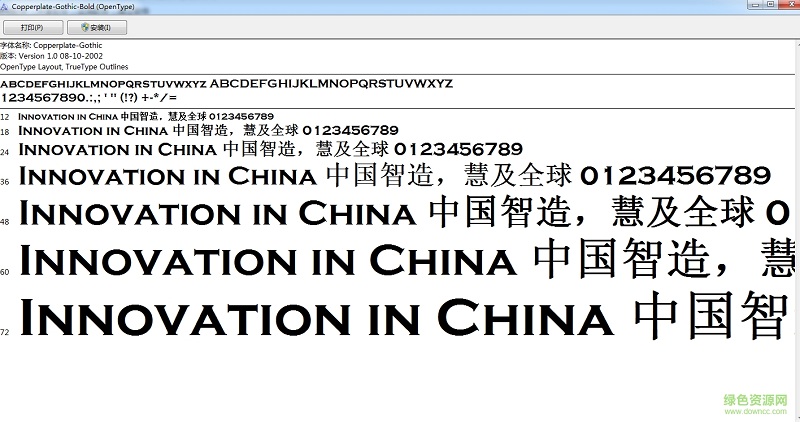
copperplate gothic bold這個(gè)字體是免費(fèi)的英文字體,字體粗黑堅(jiān)實(shí),氣勢雄健,莊重大方,表現(xiàn)力強(qiáng),喜歡的朋友歡迎在綠色資源網(wǎng)下載!
Copperplate,來源于早期銅板印刷( engraved copies)。顧名思義,是銅板或者銅板印刷。Copperplate是英文書法字體的一種。因?yàn)樗钤缡怯媚诩埳蠈懲曛?,把紙貼在金屬板上雕刻,然后復(fù)制印刷的,所以名字叫做Copperplate。